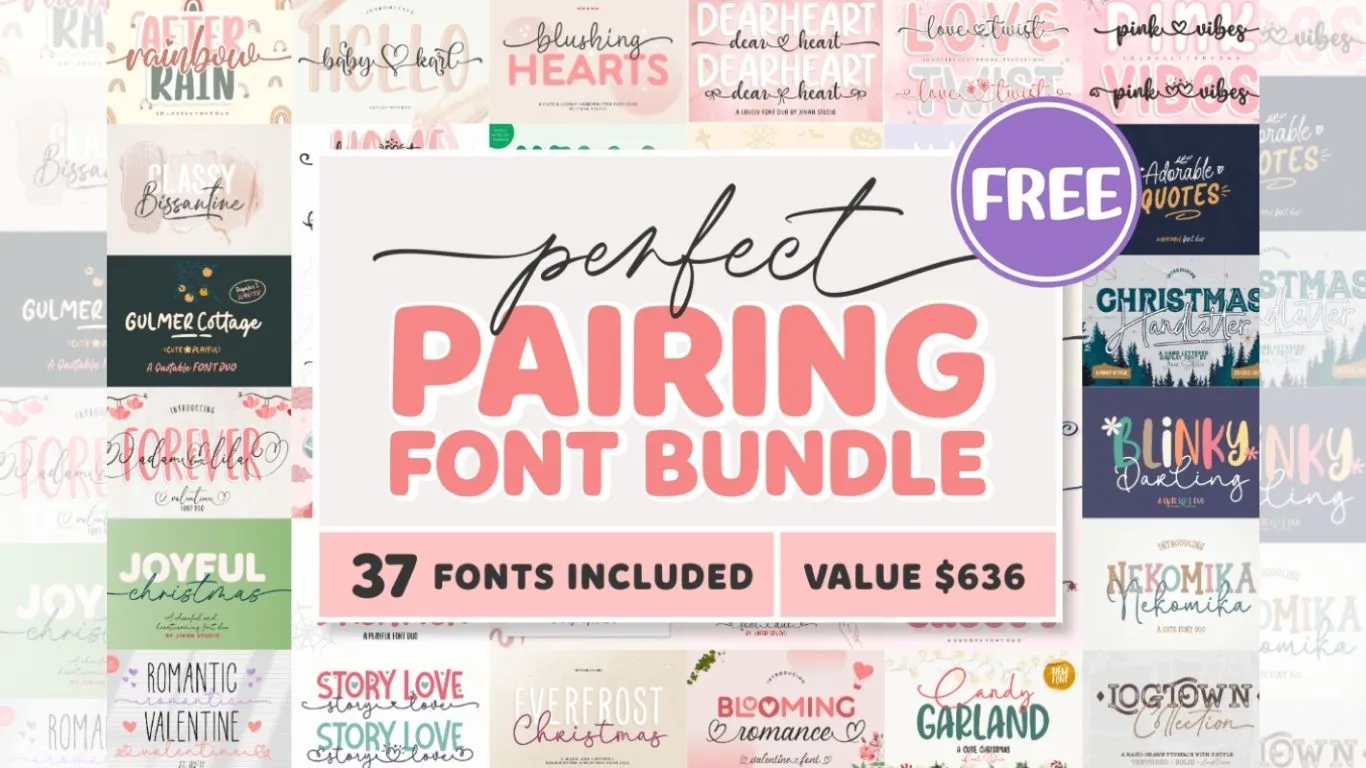
Creative Fabrica 目前正在限時免費提供一套超值的字體包 Perfect Pairing Font Bundle,有 37 款手寫與腳本風格字體,原價高達 $636 美元,現在免費!這套字體由設計師 jinanstd 精心打造,風格涵蓋浪漫手寫、節日慶祝、可愛日記等多種類型,請把握機會,趕緊收藏這套設計資源啦!
浪漫手寫 / 情人節系列
Love Twist Duo
Pink Vibes Duo
Blooming Romance Duo
Valentine Kiss Hug Duo
Romantic Valentine Duo
Adorable Quotes Duo
Blushing Hearts Duo
Beloved Angelica
Story Love
Birth of a Beauty
Forever Adam Lila Duo
Magisti Duo
日常手寫 / 可愛日記風
Dearheart
Simple Thinks
Simply Lovely
Daisy Diary
Charming Mama
Nekomika
Ameri Brian
Hello Baby Karl Duo
Mystic Dreamer Duo
Blinky Darling Duo
Home Town Duo
節慶 / 聖誕系列
Everfrost Christmas Duo
Hello Santa Duo
Memorable Christmas Duo
Christmas Handletter
Candy Garland Duo
Joyful Christmas Duo
Xmas Groovy Duo
季節 / 特殊節日
Autumn in Love Trio
Mister Pumpkins Duo (萬聖節風格)
Amazing Easter Duo (復活節風格)
Rainbow After Rain
展示標題 / 品牌風格
Logtown
Gulmer Cottage Duo
Classy Bissantine Duo